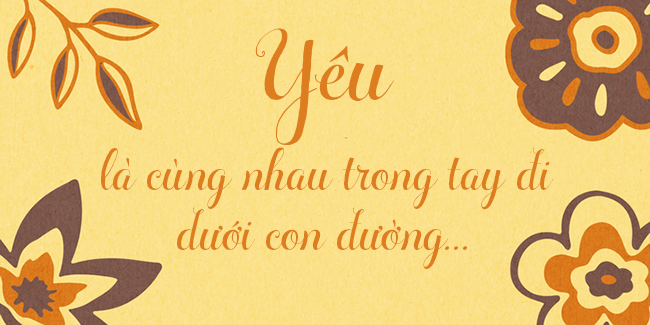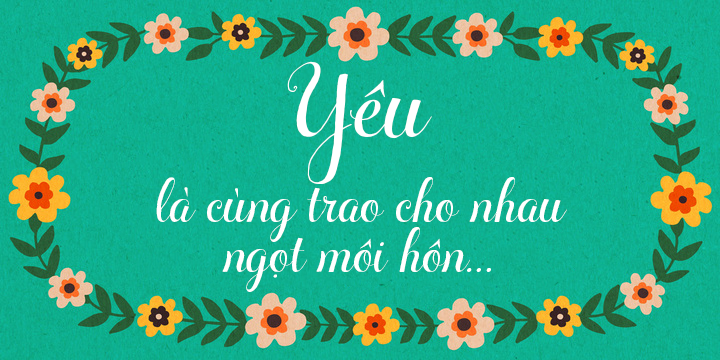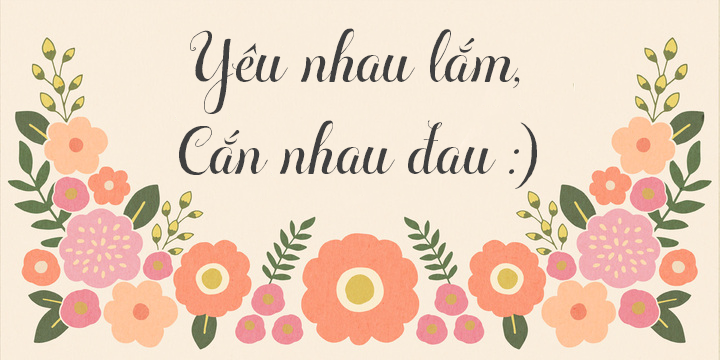
Ciao Bella của Cindy Kinash và Charles Gibbons kết hợp nét thanh lịch phá cách của kiểu chữ copperplate vẽ tay cùng bốn font ornament. Script Ciao Bella sở hữu đầy đủ bộ ký tự quốc tế và các ký tự thay thế, tận dụng sức mạnh của OpenType để tự động tạo nên cảm giác lettering thủ công chân thực.